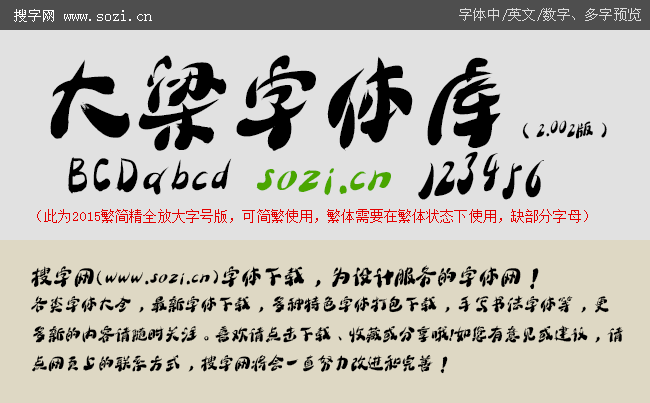
大梁字體庫(kù)2015繁簡(jiǎn)精全放大字號(hào)版
搜字網(wǎng)提供一款大梁字體庫(kù)2015繁簡(jiǎn)精全放大字號(hào)版中文書法字體下載,大梁字體庫(kù)2015繁簡(jiǎn)精全放大字號(hào)版是一款手寫風(fēng)格的書法字體,字體瀟灑大氣,整體效果非常出色,適合應(yīng)用于廣告設(shè)計(jì)、名片設(shè)計(jì)、包裝印刷、產(chǎn)品設(shè)計(jì)等應(yīng)用。